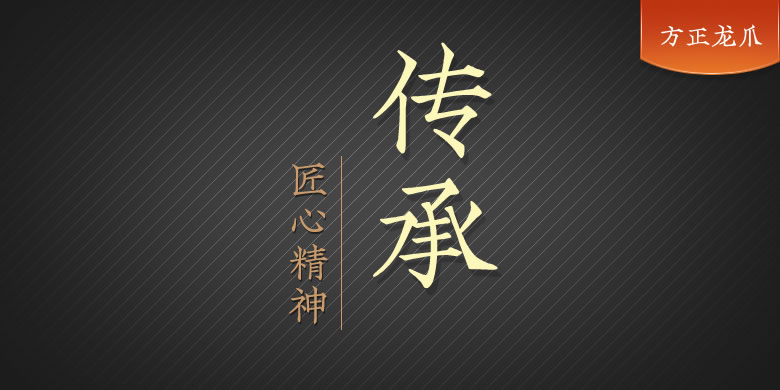
方正龙爪繁体
品牌:方正字库设计师:今田欣一发行时间:2015字库编码:大陆简体(GB2312-80)、大陆繁体(GB12345-90)分类:楷体
方正龙爪是以日本欣喜堂公司同款日文字体为基础开发的。这款字体复刻自明孝宗年间发行的儒教教义刻本《周礼》,其笔画虬枝伸展,水平方向的折笔、收笔如龙爪一样刚健,故名龙爪。按照排版要求,对方正龙爪的字形和笔形做了重新规范,并制作了中文简体字。字形风格介于硬体字和软体字之间,形态硬朗,个性鲜明。由于笔形特征突出,无论用于简短的文本还是用于包装设计,其刚劲有力的个性都会给人留下深刻印象。